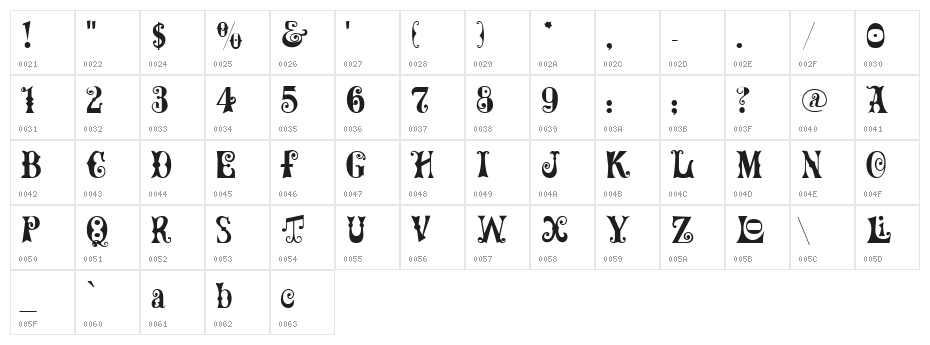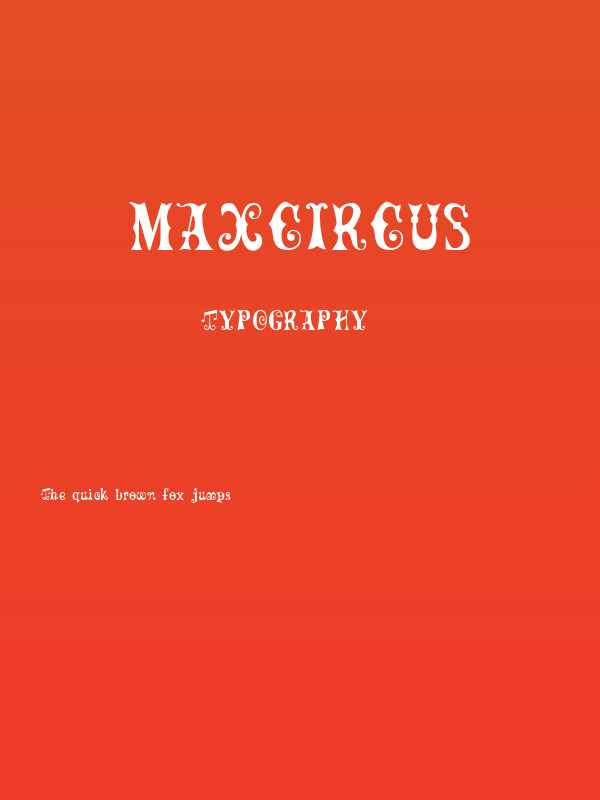
MaxCircus Font
| Gesamtstil | Vintage |
| Vorgeschlagene Projekte | Ideal for circus-themed events, playful branding, posters, and children's book covers. |